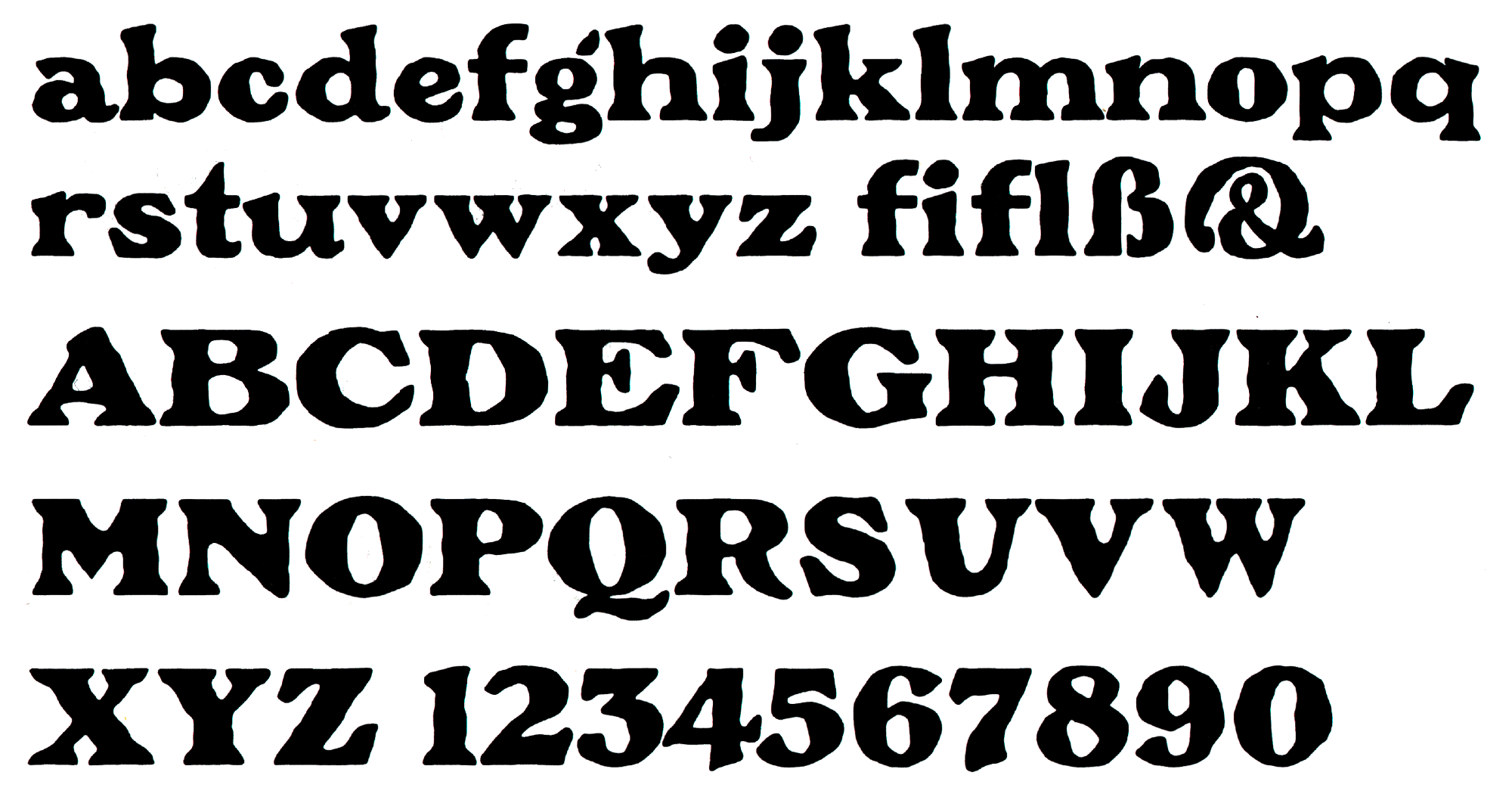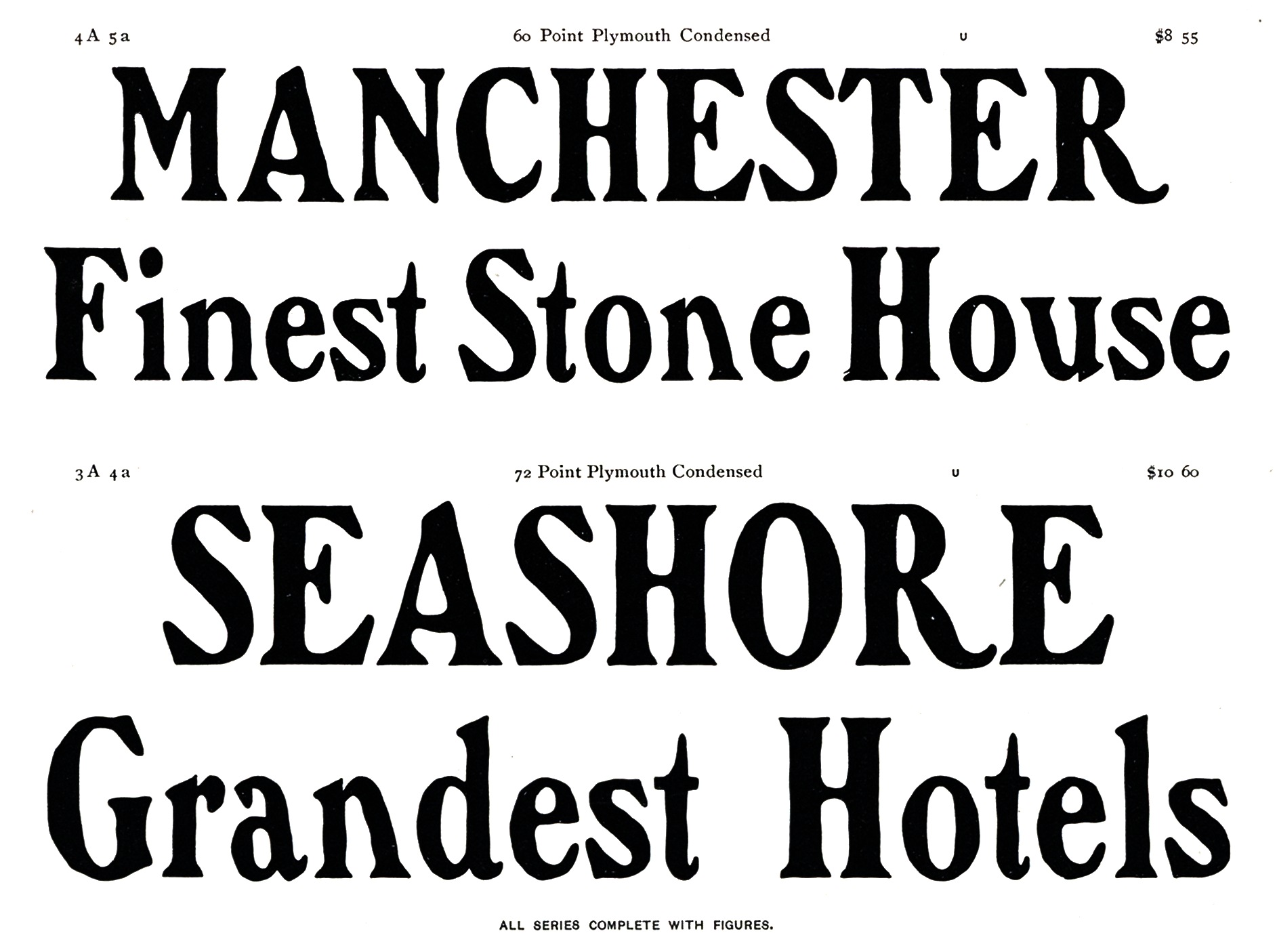
Font-Wiki: Plymouth
Die Plymouth ist eine Schriftfamilie, die Anfang des 20. Jahrhunderts bei Barnhart Brothers & Spindler erschien. Zur Familie mit der charakteristischen rauen Umrisslinie zählen ein normaler, ein kursiver, ein schmaler und ein fetter Schnitt.
Der fette Schnitt war später auch im Fotosatz erhältlich. Davon existiert heute eine kostenlose Digitalisierung.